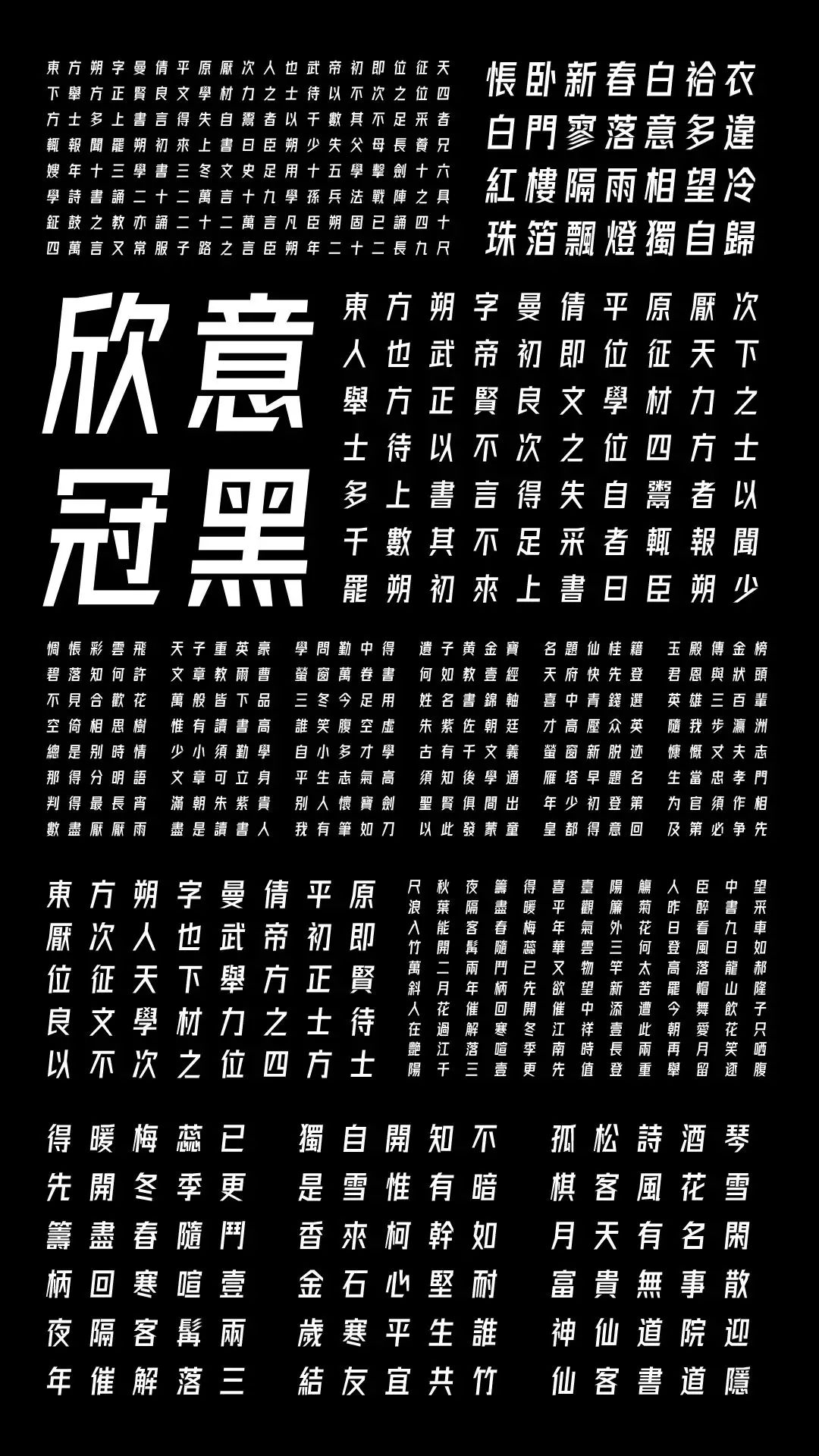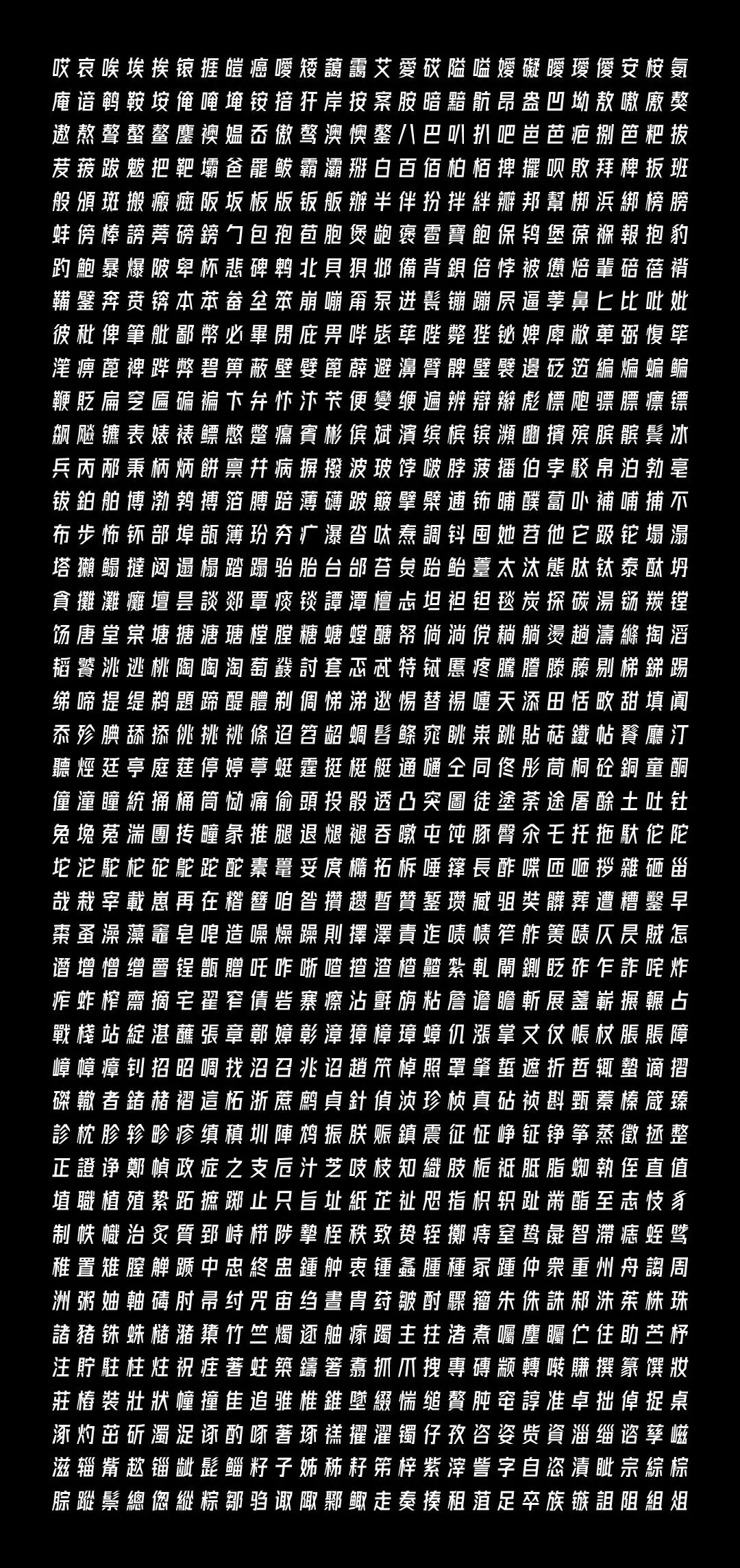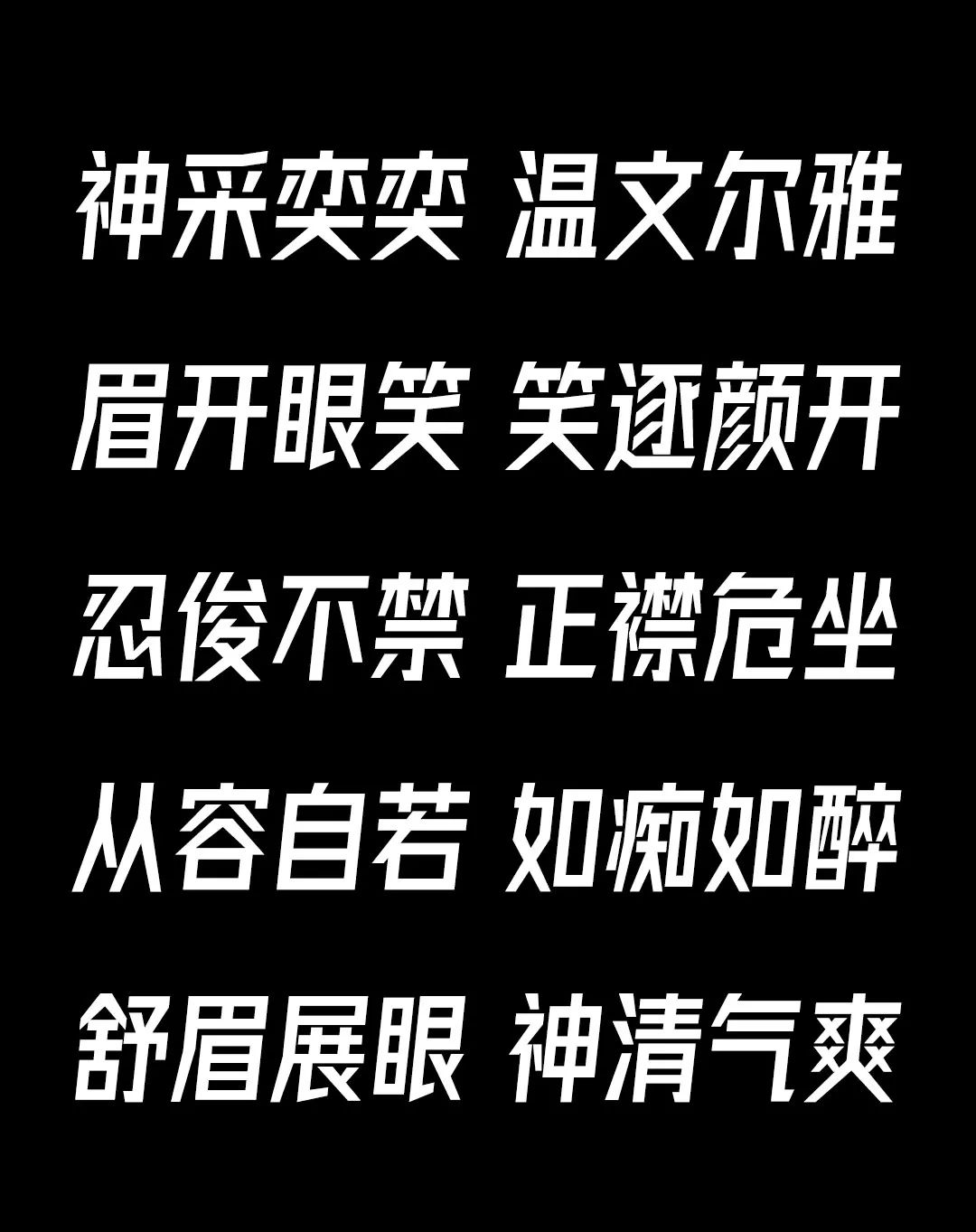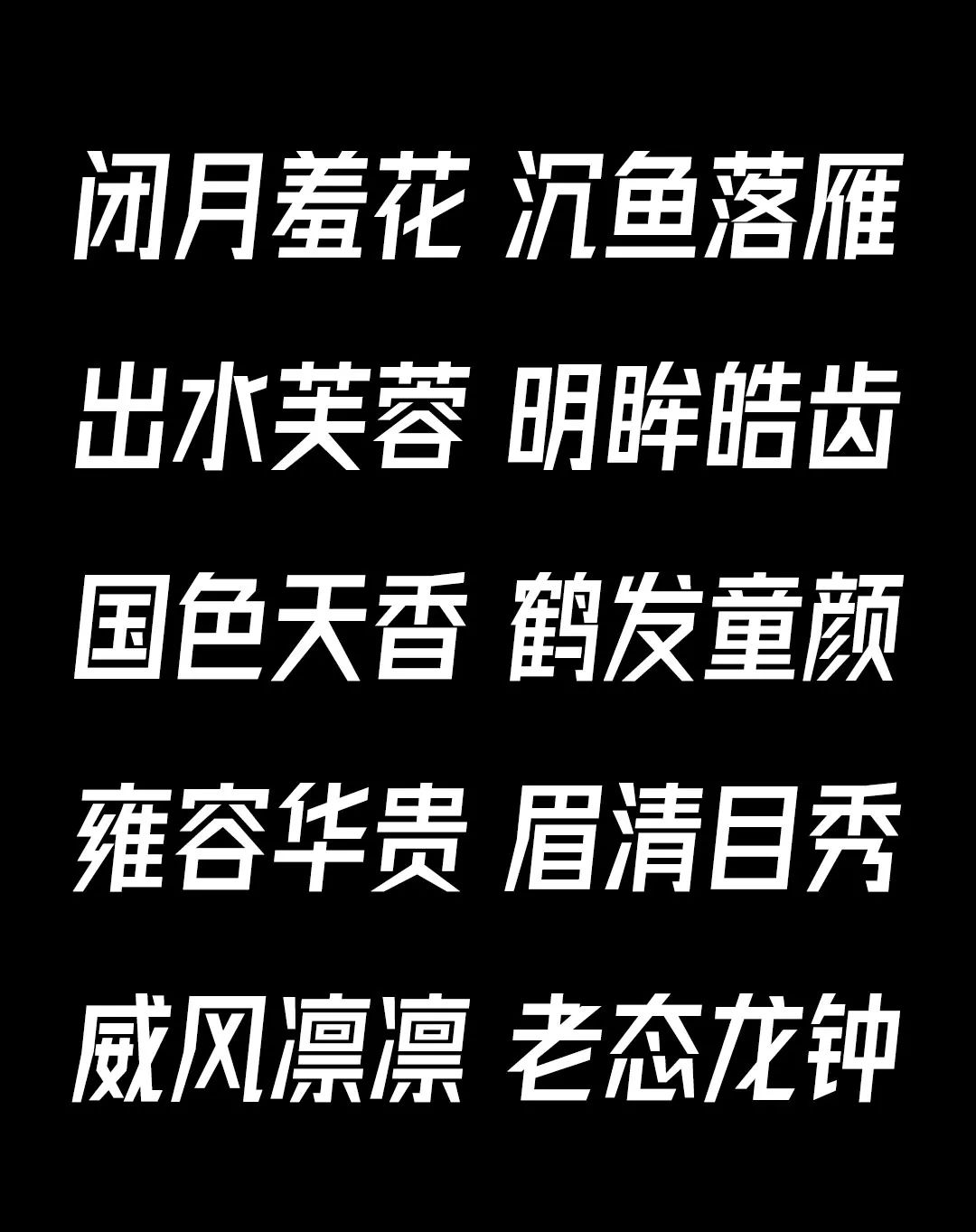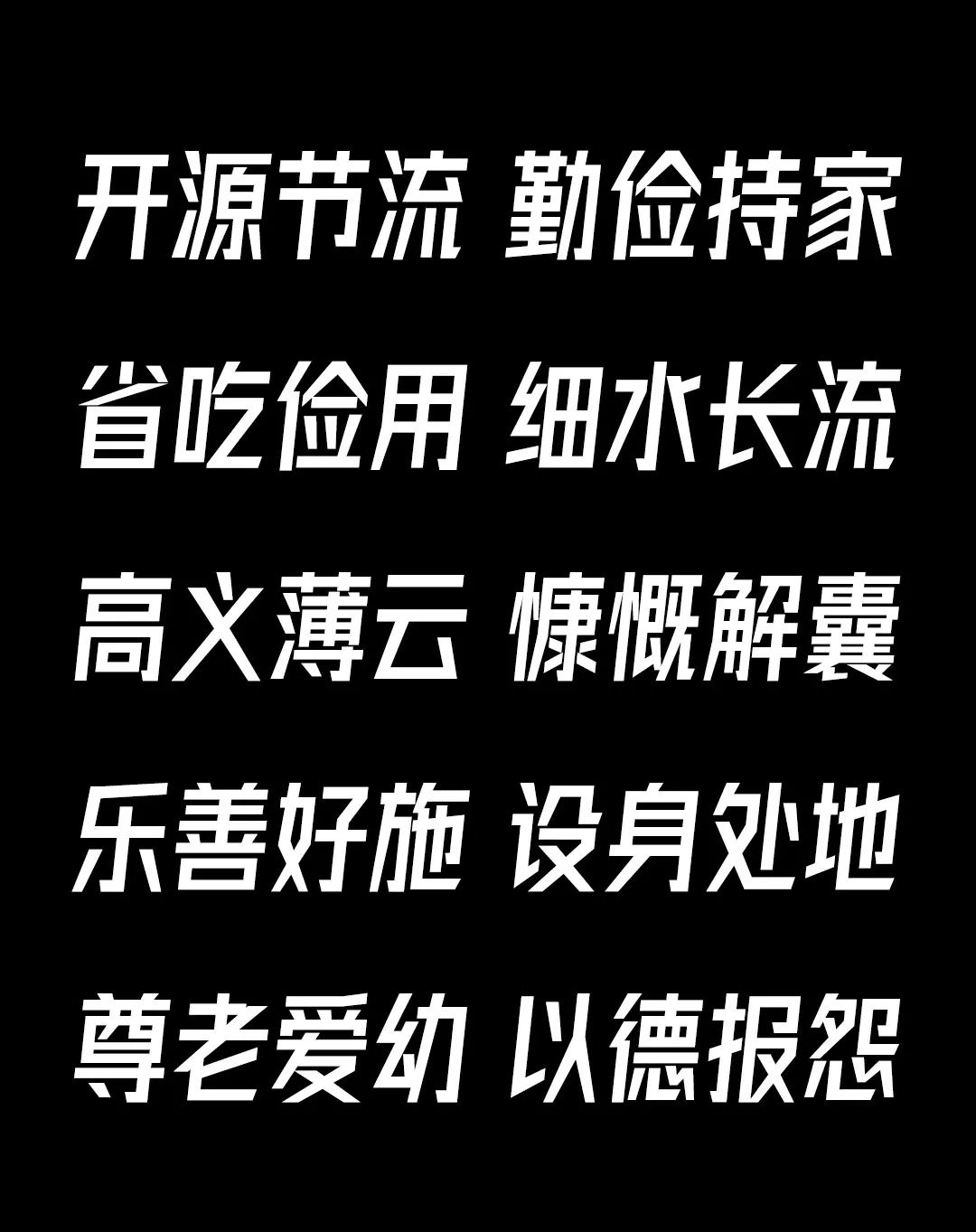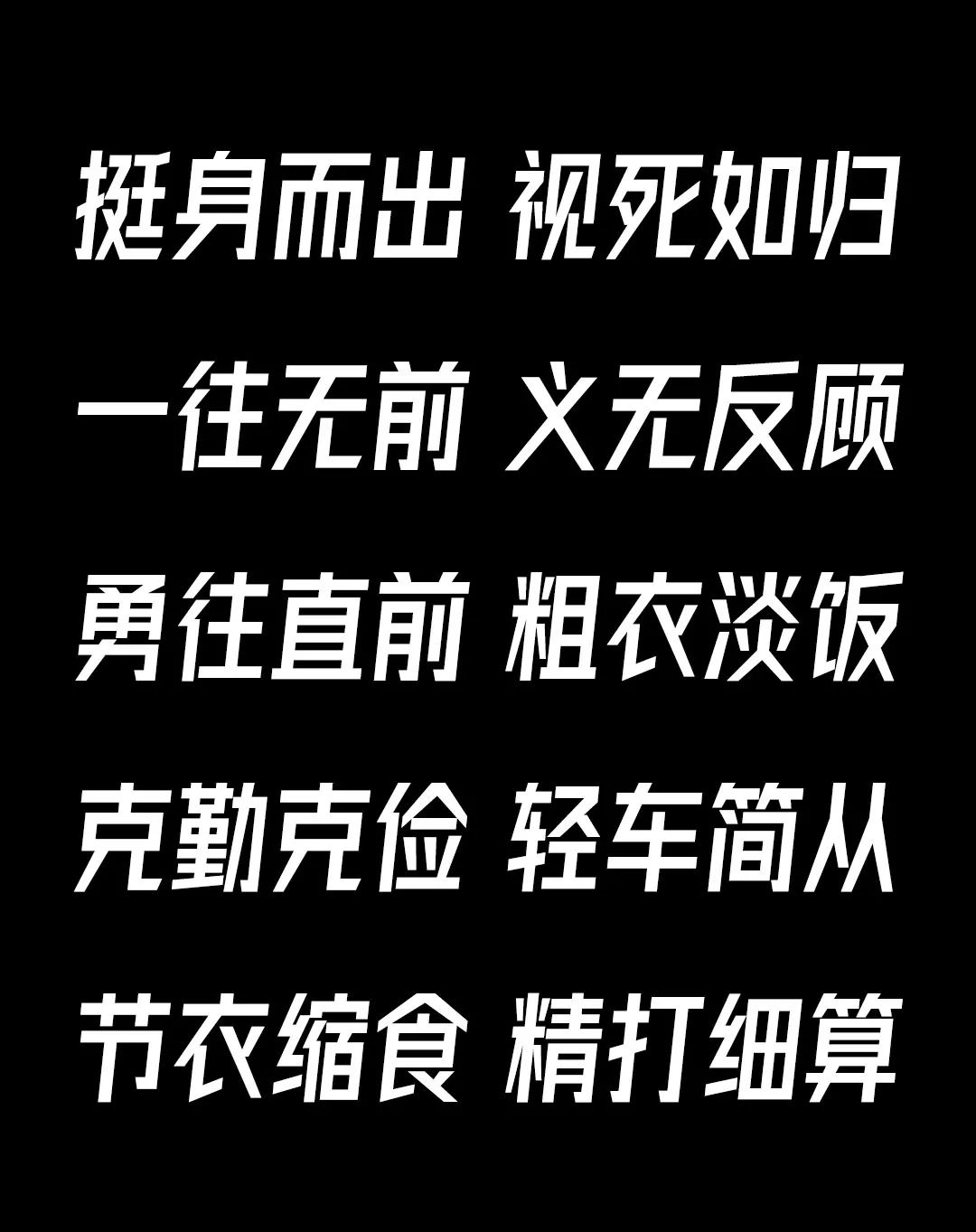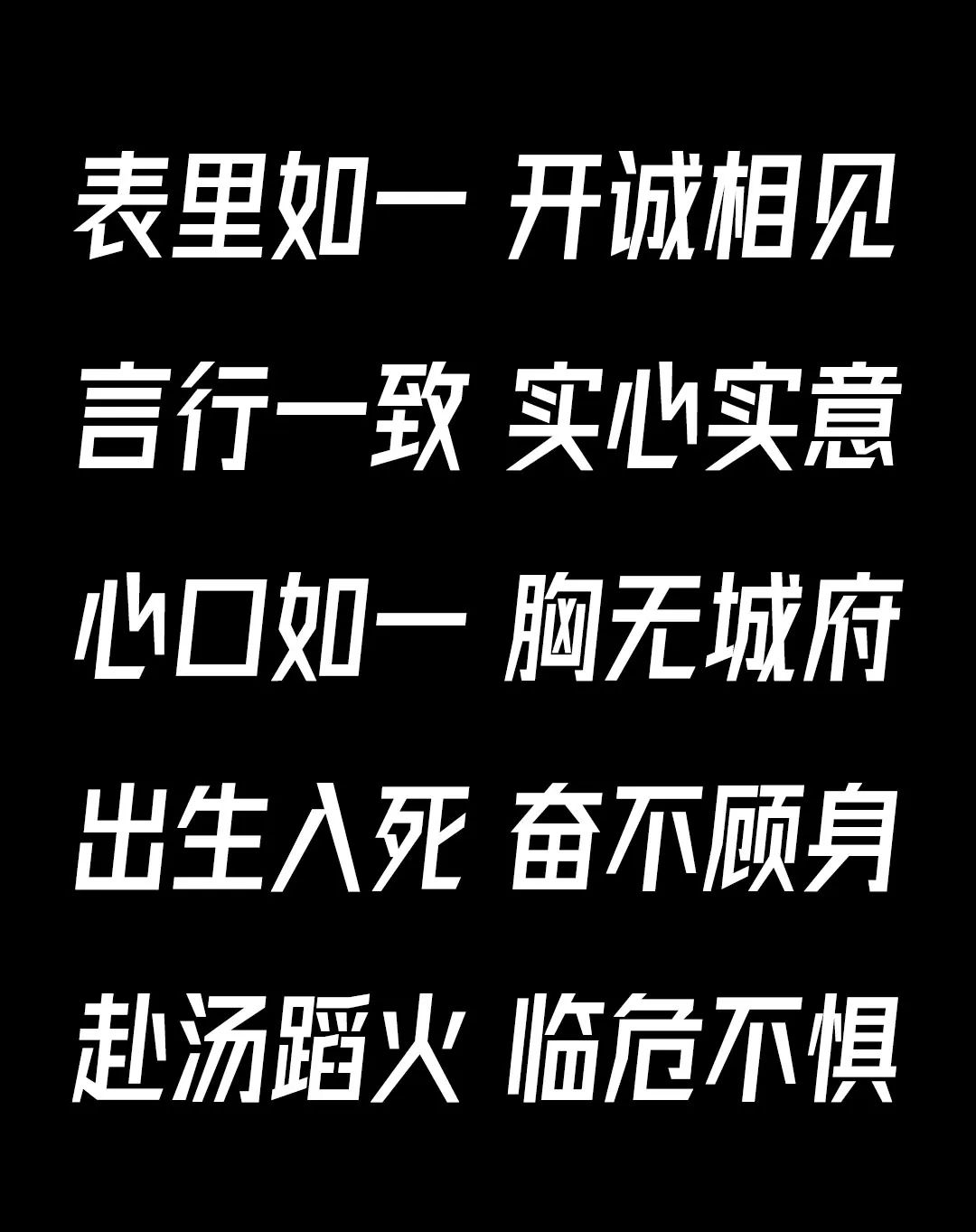
今年4月1日我发布了第一套字,也面临了很多问题,仅半个月就更新了2.0版本,当时夸下海口说不出意外3.0就是繁体版,同时也有不少的朋友跟我反应这个字的各种各样的问题,当然当时也把这些问题都解决了,重心还是在繁体设计上面。但你看完今天的文章,你会惊奇的发现,今天所更新的内容更加实用!
除了今天要更新的《字体圈欣意冠黑体3.0》以外,今天还会给大家带来第二套免费字体,后面还有其他的几款免费字也在路上,字体圈欣意系列公益字体都将会对面向全社会全媒体免费商用的。但我公众号更新很少,感谢你能把我留在你的列表,为了做这些字,其实给我带来了不少的经济压力,加上繁体花费的时间,陆陆续续的都有一年多了,不容易呀!3 添加3000+个繁体字符,现在字符数量是将近10000个了繁体部分是这次更新的重心,前前后后白天也弄晚上也弄,也花了四个月的时间。中文现涵盖9169字,另按需添加若干生僻字,56个英文10个数字,标点若干。虽然增加繁体只有三千多字,比简体少了整整一半,但是做起来比简体复杂得多,很多字的笔画非常多,甚至比简体多好几倍,所以工作量并没有想象中相应的减少。由上可以看出,简体比繁体轻松多了!这也就是为什么市场上这类的免费字库,都是只有简体版本的原因,经济损失更大,花费时间多,实际使用的人不多。
有些字形过于花哨,当时觉得这样OK了,但是后面做繁体的时候,越看越不顺眼,觉得为什么当初设计的时候要要这样处理,现在看真丑
,调整优化了之后好很多了。英文部分真的是这套字的诟病,经常看到用我的字的例子,还得自行去调整英文数字,甚至直接换了别的英文字体替代,所以我就直接把英文部分全部重新设计了,另外也把字面高以及风格调整的跟中文更匹配了,真的是英文字符虽然少,但是需要考究的方面还真不少。当时刚发布更新2.0的时候,就有留言说字体变小了,才发现真的是比1.0小了很多,既然有问题那必须解决!这个彩蛋小惊喜,其实这个字在朋友圈我已经发过了哈哈,我应该是全球首个免费字库里做这个字的了吧!!如果在我之前别的免费字库中有做了,当我没看见。目前专门针对这个字进行设计的字库是很少的,并且汉字里没有对这个字的编码,但他可以说是生僻字中的佼佼者,不比其他生僻字用的少,尤其在陕西。算是一次新的尝试吧,讲真这一个字,搞了半小时抠细节,哈哈哈。(之,穴,月,幺,言,幺,長,馬,長,刂,心)英文状态下输入biangg 即可呈现这个字!(小写哦)
这是一套全英文字库,适用于标题、LOGO设计等场合使用,所以只做了52个英文10个数字和几个标点。这套字体其实很早就做完了,当时还发了这条朋友圈,中途很多朋友问我这套字发布了没,一直没有发,就拖到现在。这套字巧妙之处在于,如果你的公司需要设计LOGO,但你不会做LOGO设计,你可以把字打出来,调个间距,调个颜色,国际化立马飙升!比如你看看下面这些案例,你就会明白,无论是互联网公司,还是服装品牌,还是玩具公司,还是食品公司,还是大型企业等等,都是很适合的!对于后面这款字的介绍少了些,但是我的朋友们反应都不错。《字体圈欣意冠黑体》《字体圈欣意LOGO体》是永久免费商用!记得发布1.0的那天晚上,因为提前设置好了准0点发送,当时非常激动,十一点半逼自己睡觉,习惯了晚睡根本睡不着,后来把微信退了,手机时间改了,去刷短视频,使我彻底忘掉这件事情,幻想另一天早上醒来阅读量上万,结果第二天醒来,打开微信一看,100都不到,哈哈哈哈哈。(这次绝对不会幻想了)本来是把这款字用来纪念2020年新冠疫情的一个载体,在别人网站抄走的文章里,很多变成了疫情期间创作的字体这怎么可能呢!从第一版本发布四月份那时候我就已经开始着手繁体设计的工作,到现在八月,大概4个月的时间,一个人完成,天天能看到凌晨四点的太阳,甚至前些日子为了加快进度,连着通宵了几天,早上七八点睡,当然上午基本是起不来的,现在回想起来,确实不比去年做1.0时轻松。虽然全程都是我设计我开发,但算上所有成本结合综合市场价值,不说多最起码几万块的成本是有的。在我刚发布时,很多朋友不理解,为什么我要做免费字体,起码收一点版权费啊,这样好歹还能捞点饭钱,算一算做的字加起来也有快10万个了,一个字1块钱也赚钱赚到手软了,但这套字从发布以来确实没给我带来任何收益。国内字库并不多,这几年版权意识越来越被重视,也随着字体设计越来越大众化,造字成本也越来越低,国内字库厂商也越来越多,但是邻国日本在2012年就已经有高达3000款字库,中国才不到500款,高质量字库更是少之又少。除了这些,正是因为国内开始重视版权,但大家还没有尊重版权的习惯,认为这些字体随便用都可以,但总是有无意侵权的例子,付出一笔不少的赔偿金(某show自媒体曾因字体侵权,赔偿10万)(某公司曾因使用雅黑,损失几千万元)(2007年某游戏侵权被索赔1个亿),这些都是对版权意识的缺失而造成的损失。有人怕我现在说免费,后面用的人多了突然开始收费,可能我之前没想过这个问题,就没说,但请大家放心,不出售给字库公司,不对外收取任何关于使用字体的费用,不做下载限制,我既然做出这些决定,肯定是还在我承受能力范围内的,永久免费商用,在最开始我就说了很多很多遍了(总有人加我微信问我)。创作不易,如果有更多热爱字体的朋友愿意参与字体制作,可以私信我,毕竟对我来说这是一件很酷的事情。另外你有原创字/手写字/毛笔字,我可以免费为你做封装的工作,前提是开发出来最终做面向大家是免费商用的,也可以在这里为你发布。字体版权声明:本次发行的字体《字体圈欣意冠黑体》《字体圈欣意LOGO体》,已在国家版权局登记认证。使用范畴说明:允许任何个人和企业免费使用,包括商用用途。但不得单独或者附带地以出售、出租、出借等方式向公众发行以获取利益。同时不得对本字库软件进行修改、仿制、反编译、转换、拆分等行为。